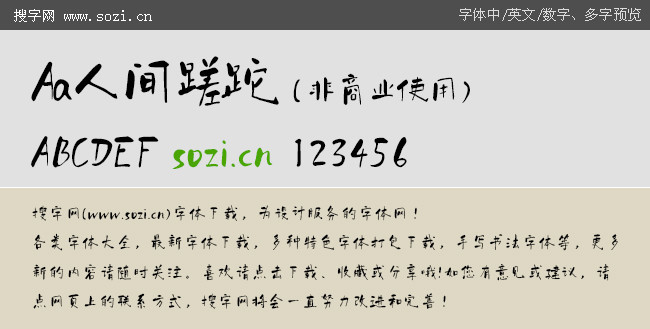
Aa人間蹉跎
搜字網(wǎng)給大家提供一款A(yù)a人間蹉跎(非商業(yè)使用)中文字體下載,該字體是一款手寫書(shū)法字體,字體書(shū)寫時(shí)粗時(shí)細(xì),書(shū)寫流暢,給人一種非常舒服的視覺(jué)感受,適用于平面宣傳設(shè)計(jì)、網(wǎng)頁(yè)設(shè)計(jì)、海報(bào)設(shè)計(jì)等應(yīng)用(此字體為個(gè)人非商用版,商用可以聯(lián)系QQ:1006760504)。